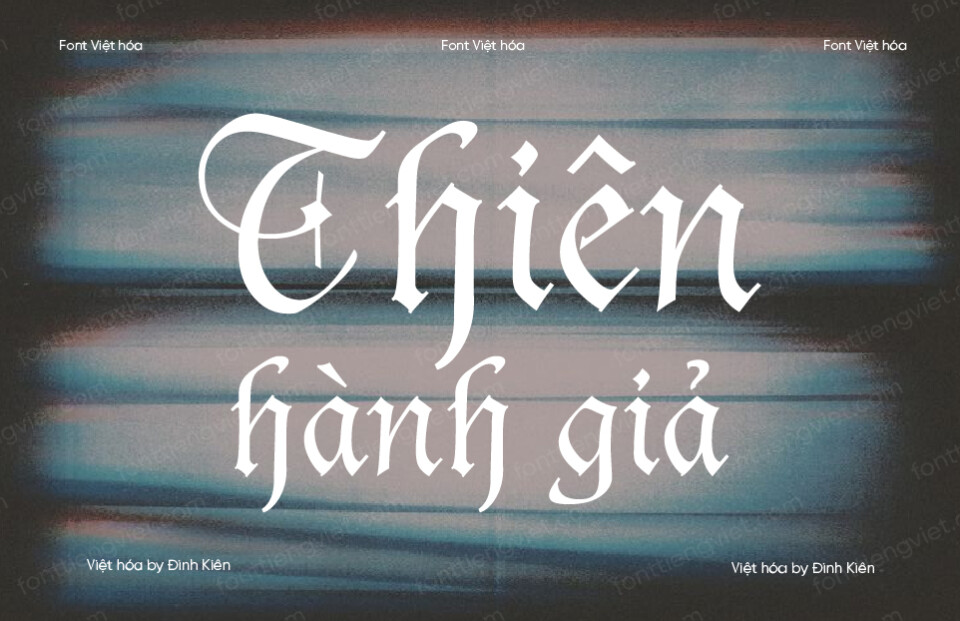
Font Việt hóa UTM Duc De Berry: Nét chữ cổ điển đầy sang trọng cho thiết kế
Khám phá Font Việt hóa UTM Duc De Berry là một hành trình tìm về vẻ đẹp quý tộc và cổ điển của nghệ thuật thư pháp châu Âu. Đây là bộ Font Chữ đặc biệt phù hợp cho các bạn học sinh và nhà trường khi thực hiện các dự án thiết kế thiệp mời, bằng khen hoặc bìa sách nghệ thuật. Với các đường nét uốn lượn tinh xảo, font chữ này không chỉ mang lại giá trị thẩm mỹ cao mà còn giúp thông điệp truyền tải trở nên trang trọng và ấn tượng hơn trong mắt người xem.
Đặc điểm nổi bật của Font Việt hóa UTM Duc De Berry
Phong cách Gothic hoài cổ
Font Việt hóa UTM Duc De Berry mang đậm dấu ấn của phong cách Gothic truyền thống với các nét đậm nhạt tương phản rõ rệt. Cấu trúc chữ cái được chăm chút tỉ mỉ, gợi liên tưởng đến những bản thảo cổ viết tay bằng lông ngỗng. Chính sự cầu kỳ này đã biến nó thành lựa chọn hàng đầu cho các thiết kế mang tính lịch sử hoặc tâm linh.
Khả năng tương thích tiếng Việt hoàn hảo
Điểm cộng lớn nhất là bộ font này đã được Việt hóa chỉn chu, giúp khắc phục hoàn toàn lỗi hiển thị dấu câu thường gặp ở các font nước ngoài. Các thầy cô và học sinh có thể dễ dàng soạn thảo các văn bản tiếng Việt mà vẫn giữ được sự hài hòa trong bố cục tổng thể của con chữ.
Ứng dụng Font Việt hóa UTM Duc De Berry trong học tập
Trong môi trường giáo dục, việc sử dụng font chữ này giúp các em học sinh rèn luyện tư duy thẩm mỹ. Bạn có thể dùng nó để trang trí báo tường, làm tiêu đề cho các bài thuyết trình lịch sử hoặc tạo ra những tấm thiệp tri ân thầy cô giáo đầy ý nghĩa. Sự kết hợp giữa nét cổ xưa và hiện đại tạo nên một phong cách cá nhân độc đáo.